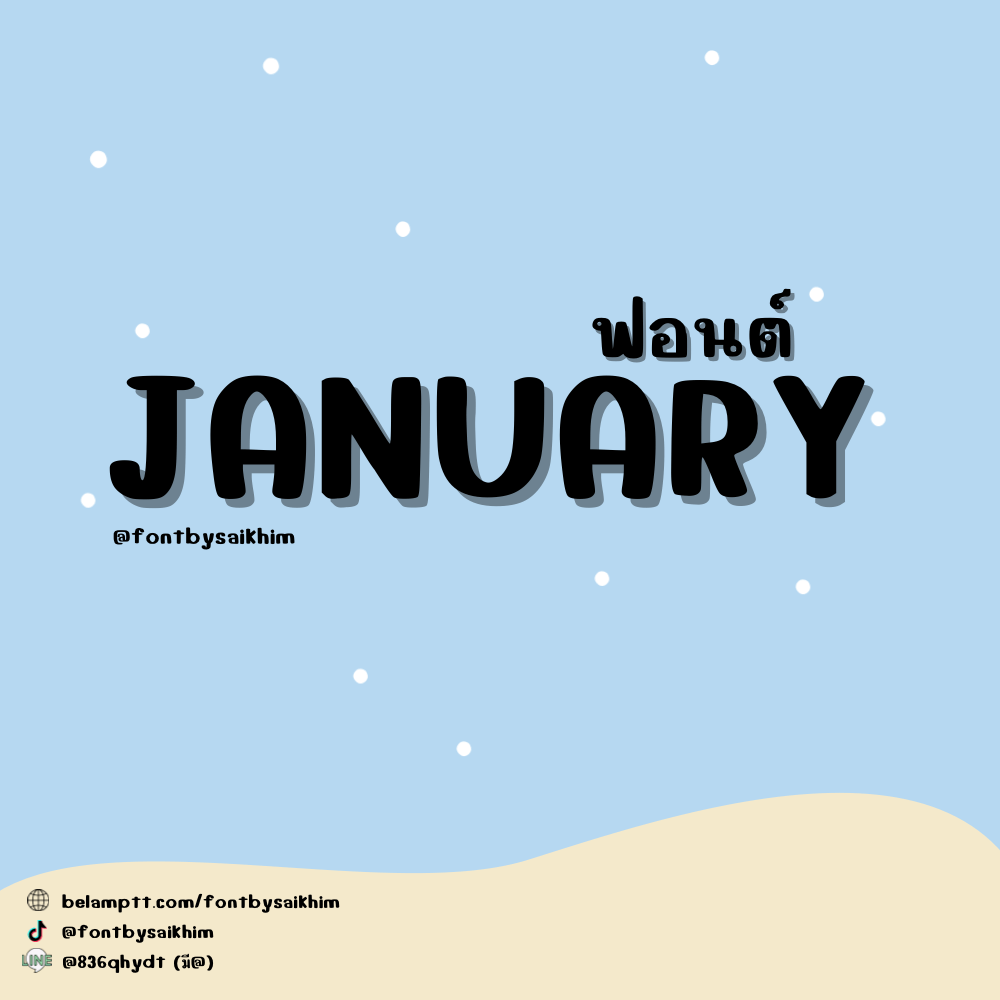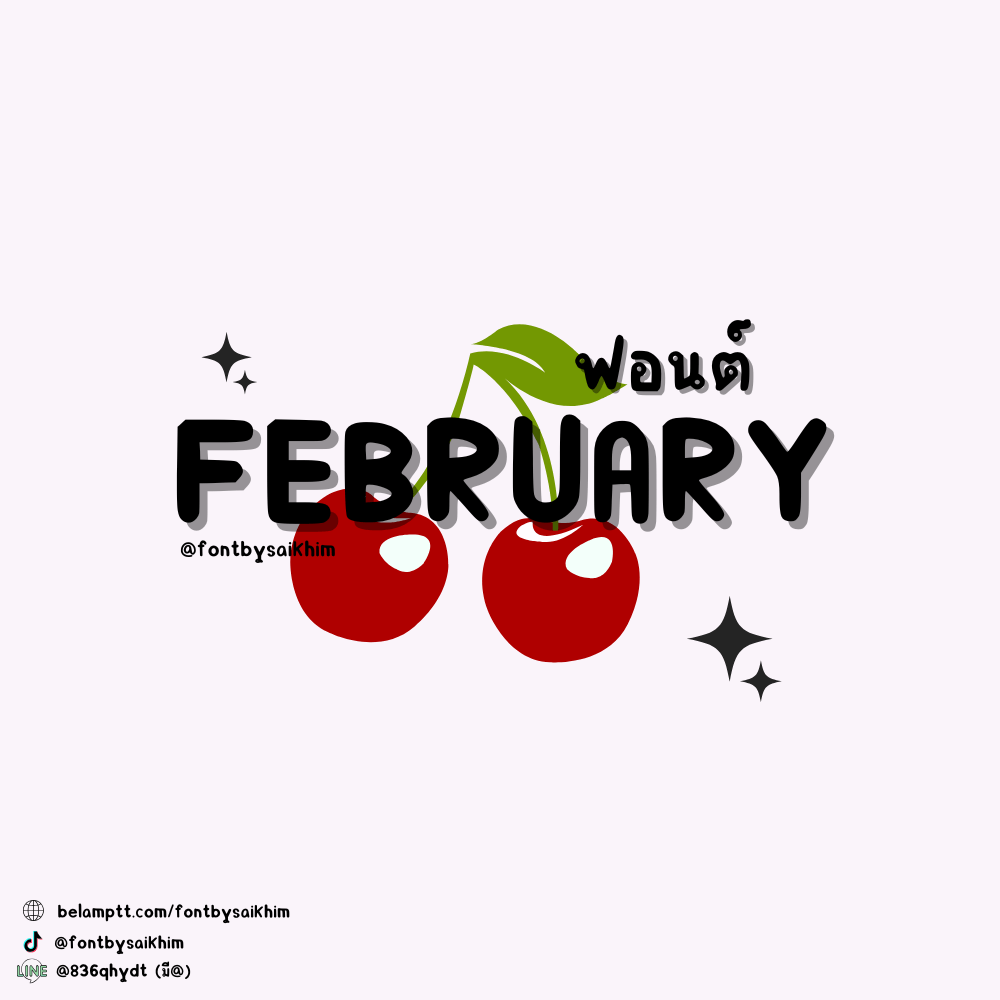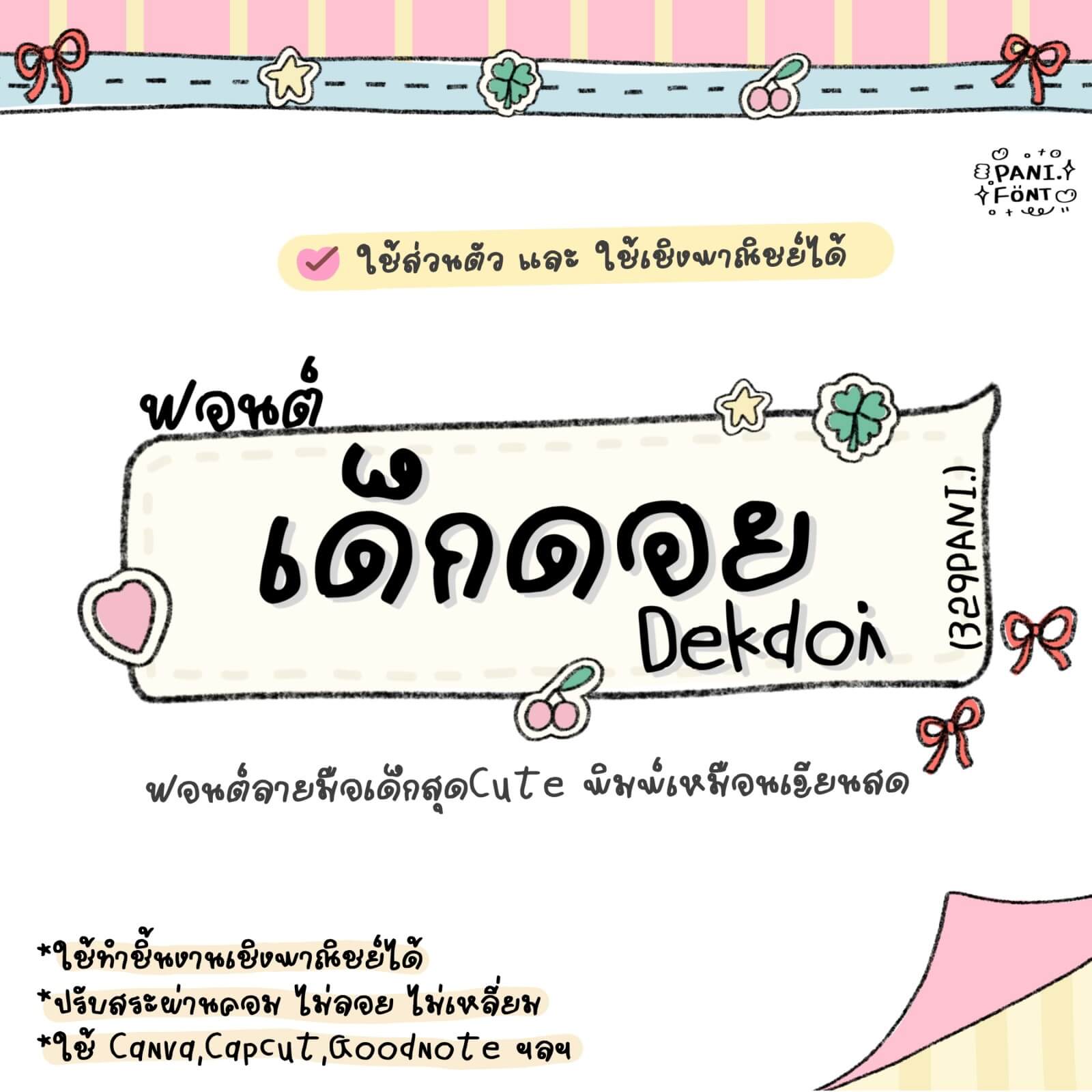
ฟอนต์ลายมือไม่มีหัว มีด้วยกัน 3 น้ำหนัก คือ บาง ปกติ หนา นูร่าราดาเปิดให้ใช้ฟรีงานส่วนตัวและงานทั่วไป น้ำหนักบาง
ฟอนต์ 329PANI.Dekdoi – โหลดทดลองใช้ฟรีตัว Demo ใครชอบแนว ลายมือเด็ก หรือแต่งรูป แต่งคลิป ทำคอนเทนต์ คือน่ารัก หรือจะเอาไว้จดใน Goodnote ก็เหมือนเขียนสด เหมือนเขียนเอง รับรอง ชุดนี้ไม่ผิดหวัง
ฟอนต์ เฟบบูรี (SK February) ทดลองใช้ฟรีสำหรับงานส่วนตัวที่ไม่สร้างรายได้ เวอร์ชันทดลอง (demo) น้ำหนักฟอนต์ไม่เท่ากัน
ฟอนต์เฟิร์สคลาส (TCS4FirstClass) ฟอนต์เรียบร้อย เจาะหัวกลม มีความเหลี่ยมๆ นิดหน่อย
ฟอนต์ แจนยัวรี่ (SK January) ทดลองใช้ฟรีสำหรับงานส่วนตัวที่ไม่สร้างรายได้ เวอร์ชันทดลอง (demo) น้ำหนักฟอนต์ไม่เท่ากัน